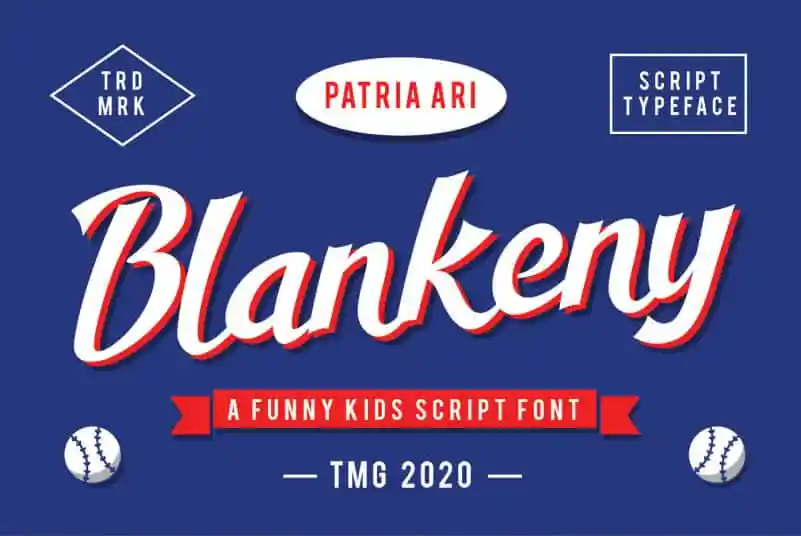
A Blankeny Script Font é uma elegante tipografia script inspirada nos designs vintage do esporte de beisebol, com toques divertidos que prometem tornar seu design mais autêntico e moderno ao mesmo tempo. Combinando a essência nostálgica dos desenhos antigos dos estádios onde os grandes jogadores brilharam com um toque atual e descontraído que combina perfeitamente para criar uma experiência visual única. Esta fonte é ideal para qualquer projeto gráfico que valorize detalhes e histórias, seja em logotipos, cartazes ou editoriais de revistas, Blankeny Script Font traz um brilho especial à sua próxima obra-prima de design.